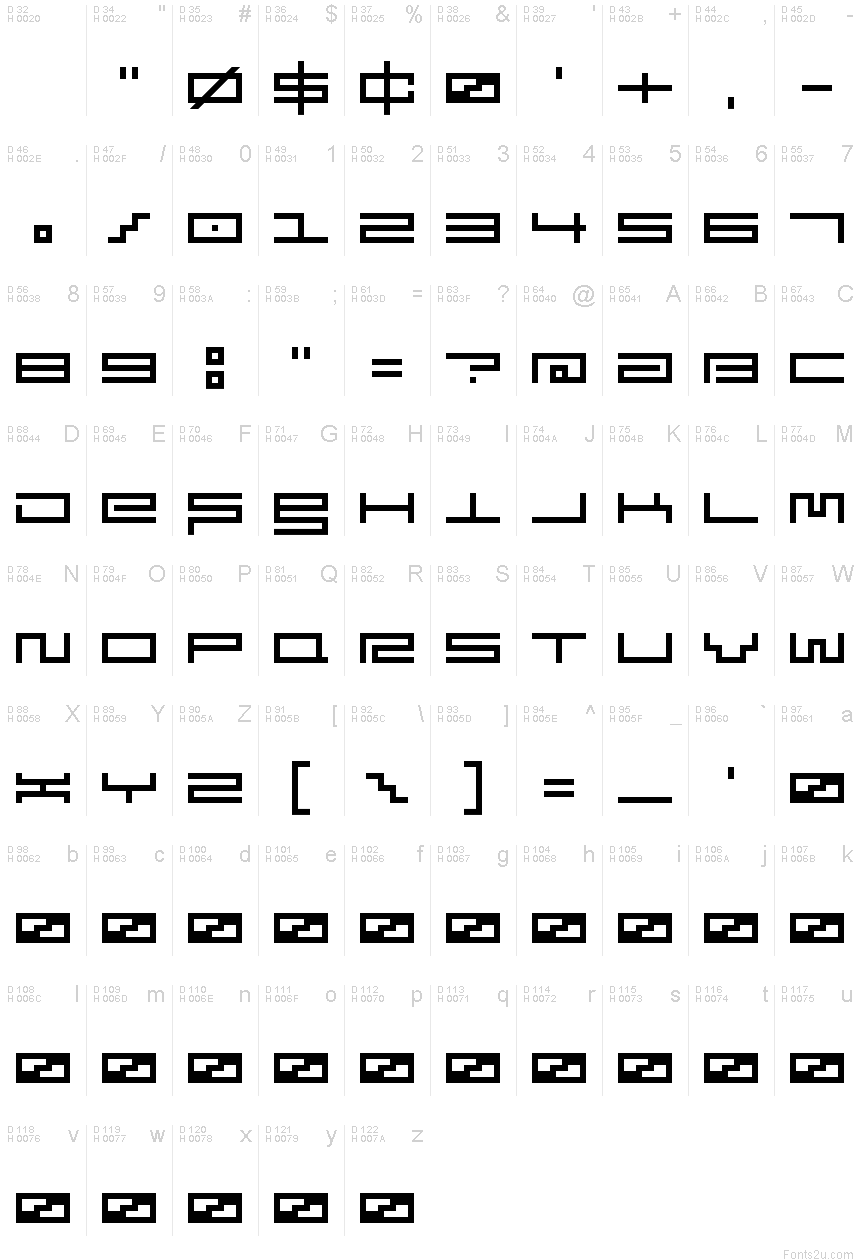
Squarepusher V3 to darmowy font bitmapowy w stylu wczesnych cyfrowych technologii. Litery zredukowano do masywnych, prostokątnych bloków pikseli ze schodkowymi narożnikami, wyraźnymi przerwami i modularnym rytmem, który bardziej przywodzi na myśl sprzęt komputerowy i grafikę z ery trackerów niż gładkie, współczesne kroje pisma.
To naturalny wybór do nagłówków interfejsów gier, ulotek techno, tytułów w zinach, plakatów stylizowanych na kod oraz krótkich logotypów, gdzie surowa, siatkowa tekstura wykonuje całą pracę. Jako darmowy font świetnie sprawdza się na kartach tytułowych, etykietach ekranów ładowania i w kompaktowych elementach identyfikacji wizualnej, ponieważ blokowe formy pozostają wyraziste i graficzne nawet w bardzo krótkich tekstach.